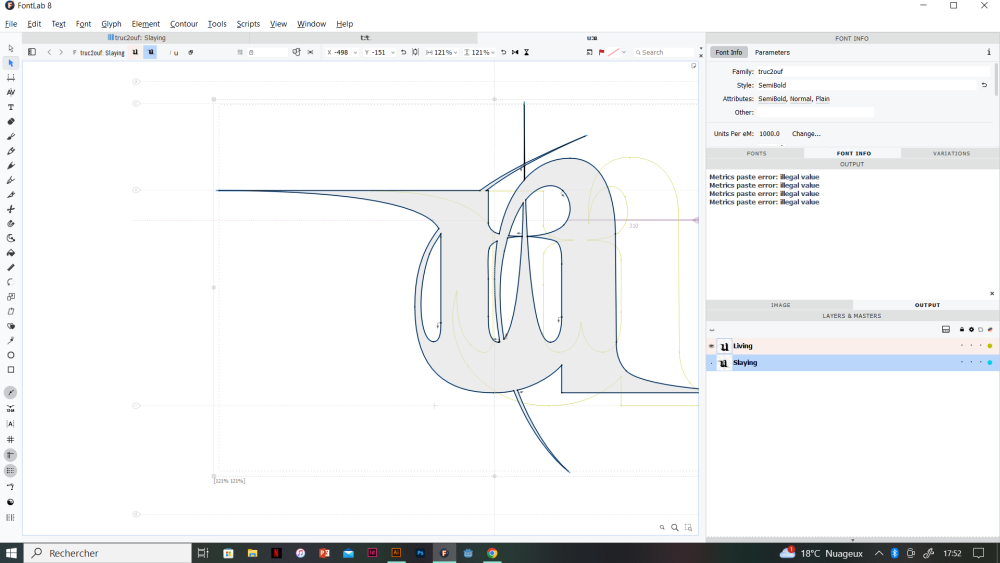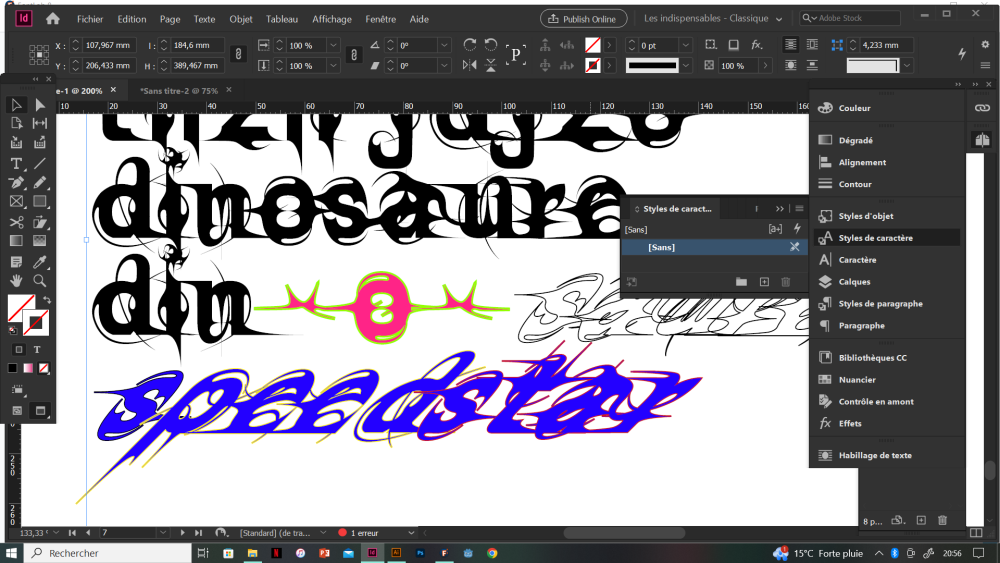
Entre une rose et un scarabée, inspirée de l'ouvrage Rose2Rage de Théophylle Dcx, la dragonne est une typographie variable camp acérée. Ses épines s'allongent et se rétractent en fonction de la graisse. Livin' or Slayin'. Elle met en exergue l'acidité d'une défense nécessaire.
Dragonne